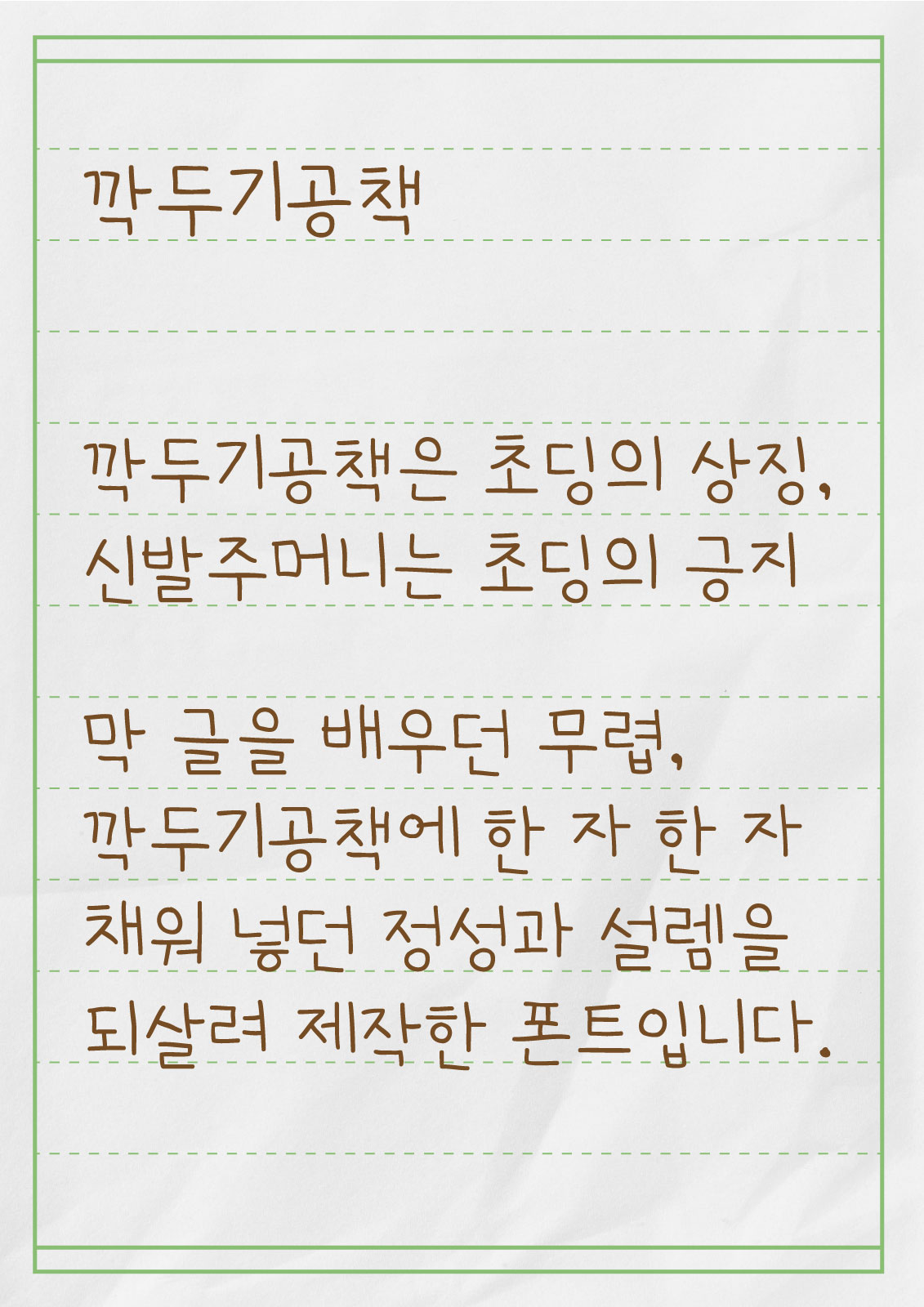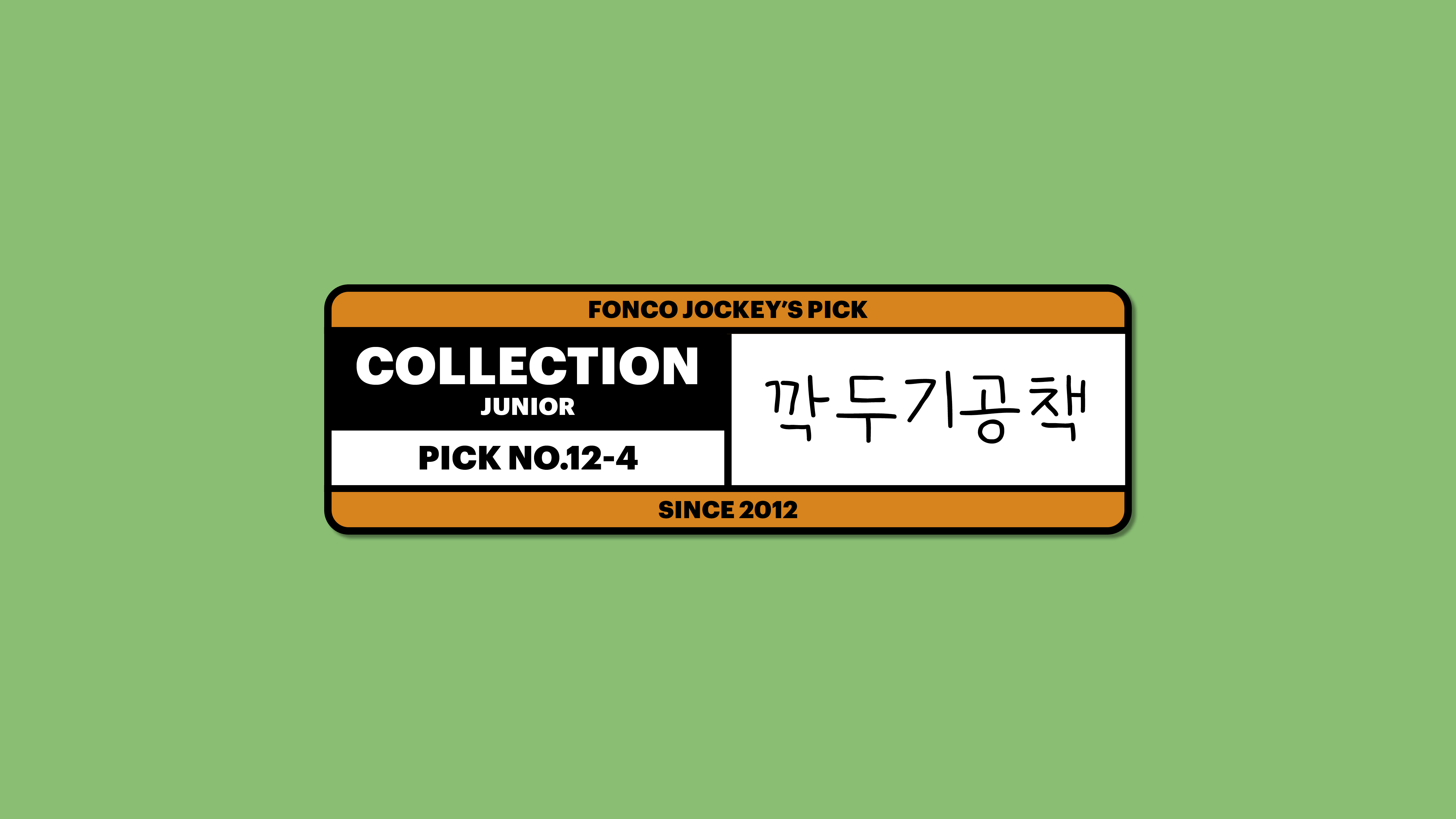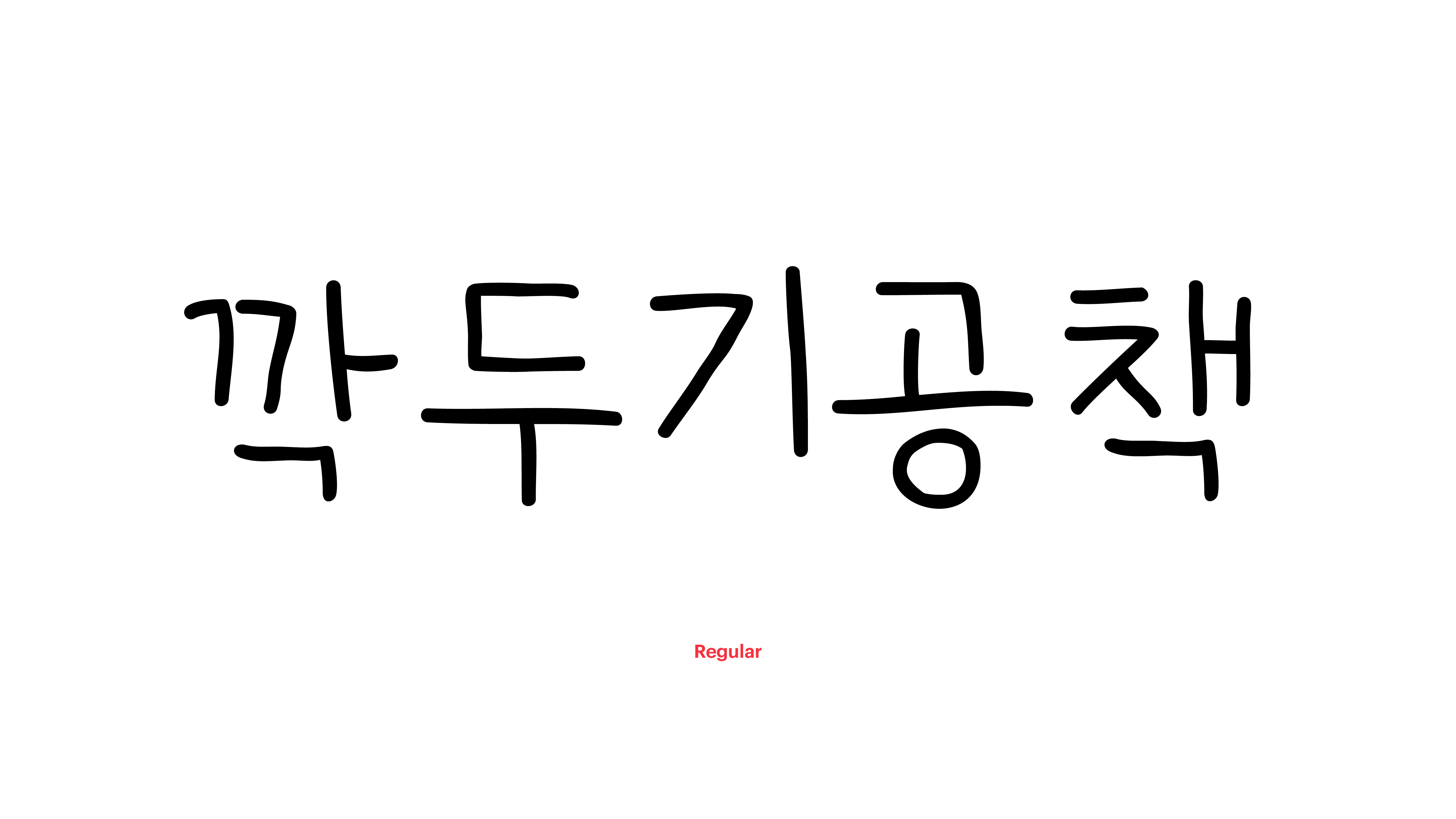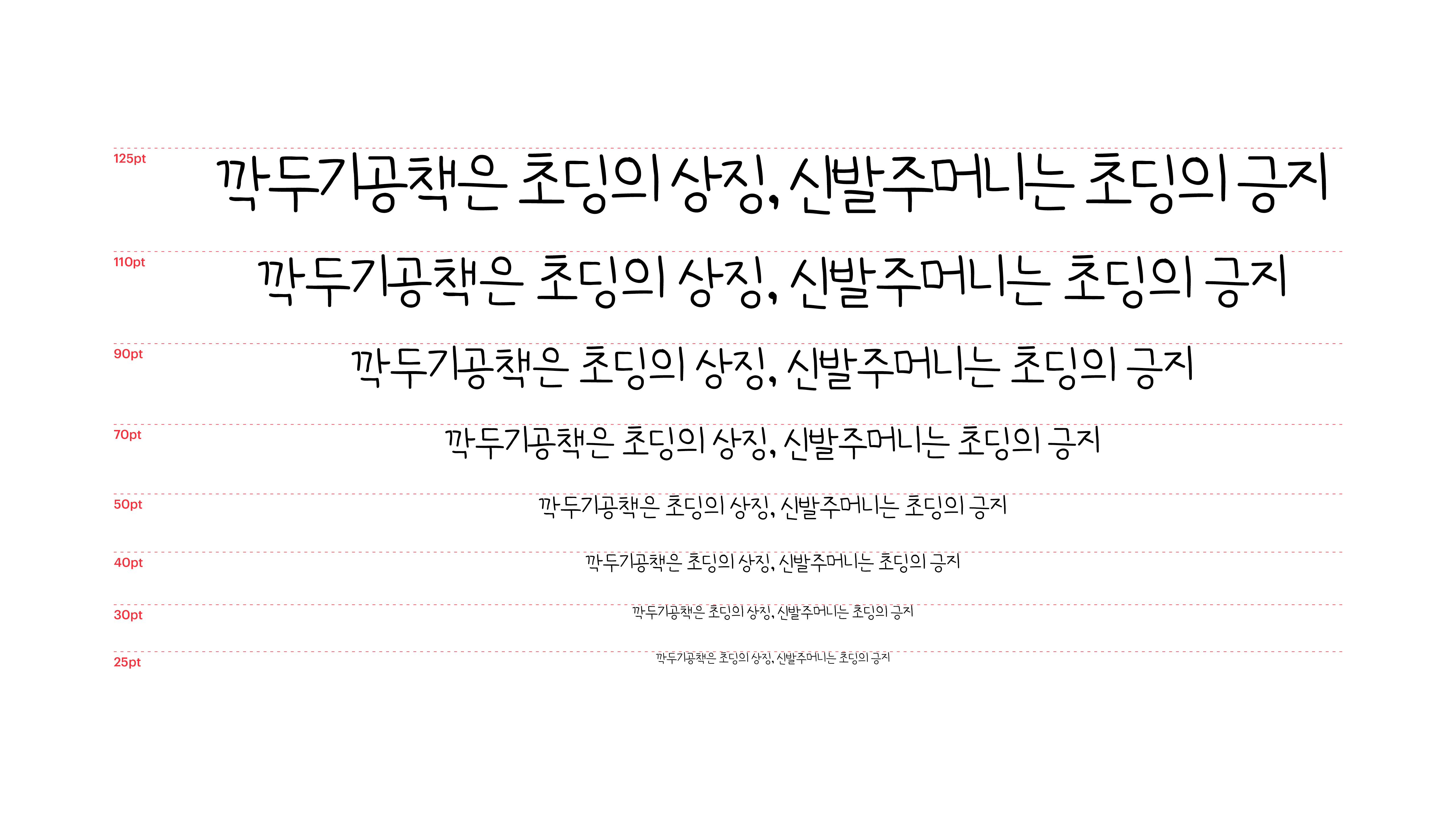
막 글을 배우던 무렵, 깍두기공책에 한 자 한 자 채워 넣던 정성과 설렘을 되살려 제작한 폰트입니다. 우리 모두의 아련한 첫 순간을 떠올리게 하지요. 하지만 가끔은 이런 이야기도 들어요. 거짓말! 난 이렇게 글씨를 잘 쓰지 않았는걸. 음, 생각해보니 폰코도 엄청난 악필에 개구쟁이였어요. 그때 깍두기공책체를 알았더라면 조금은 덜 혼났을까요?
Yoon 깍두기공책